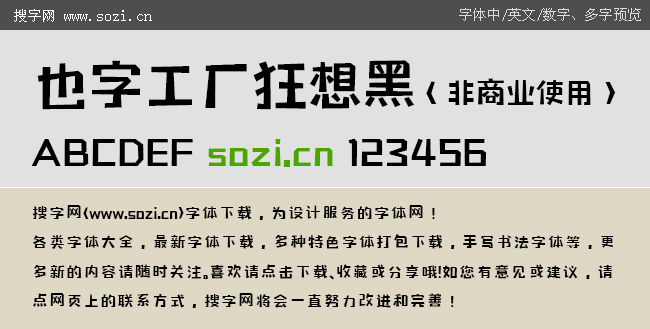
也字工廠狂想黑
搜字網(wǎng)給大家提供一款也字工廠狂想黑(非商業(yè)使用)中文字體下載,也字工廠狂想黑是一款藝術(shù)黑體字體,字體以黑體做為基礎(chǔ)字體,筆畫富于變化,使字體看上去生動(dòng)有趣,具有很好的視覺效果。適合應(yīng)用于兒童繪本、兒童海報(bào)、網(wǎng)頁設(shè)計(jì)等應(yīng)用(此字體為個(gè)人非商用版,商用可以聯(lián)系:官方網(wǎng)址:https://yefont.com/home,聯(lián)系方式:13798980448)。